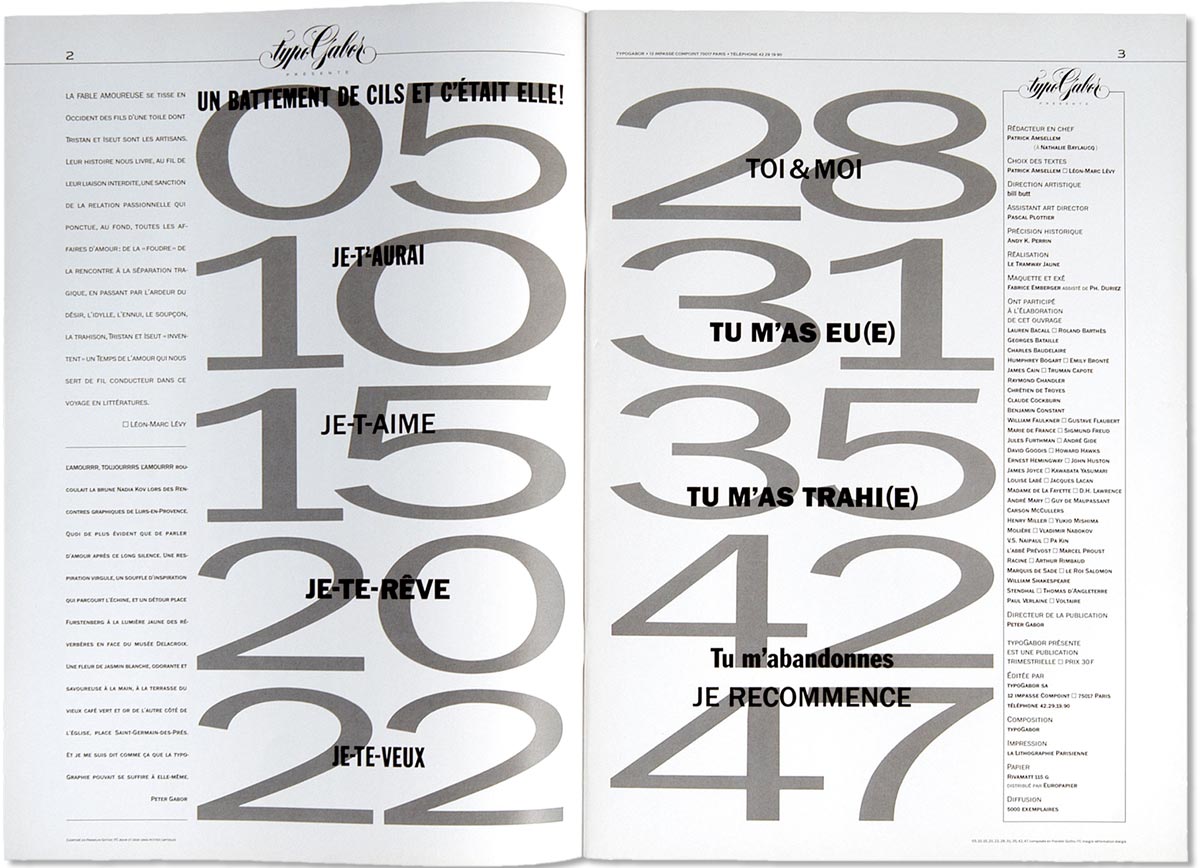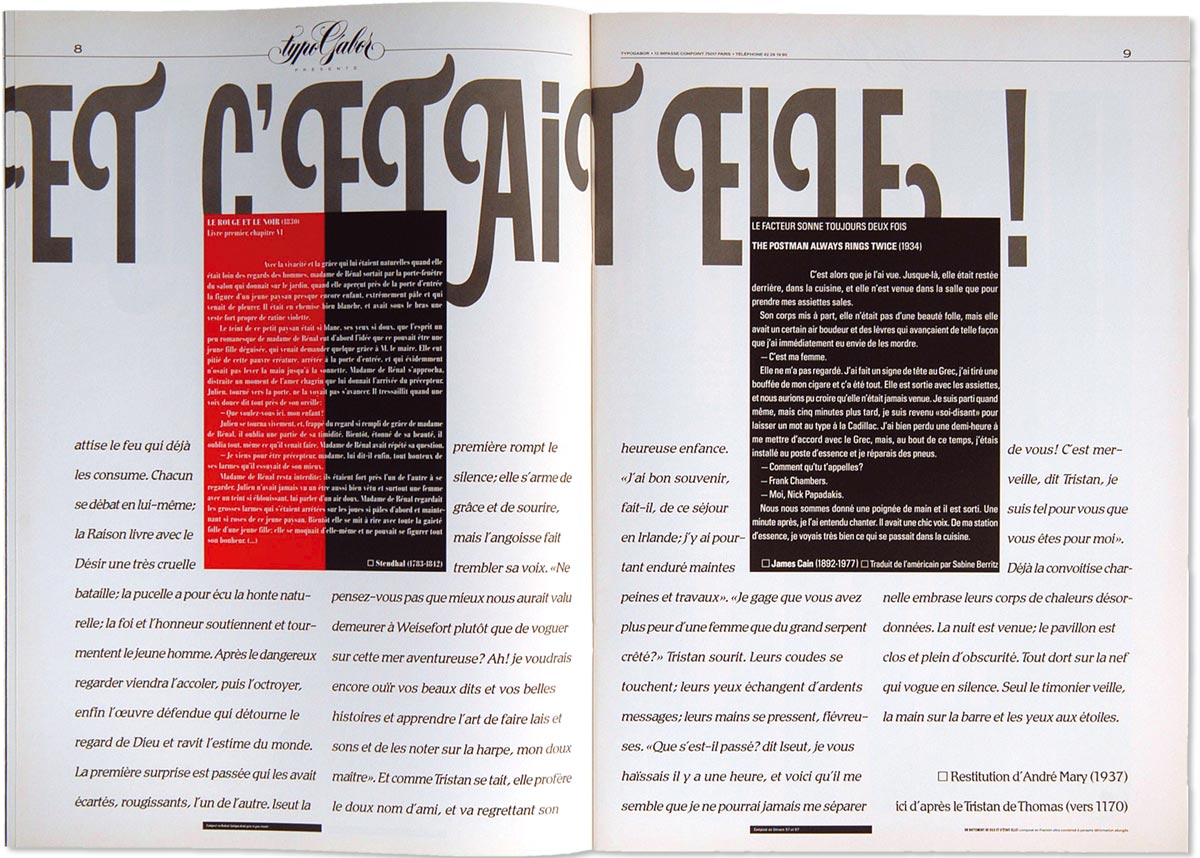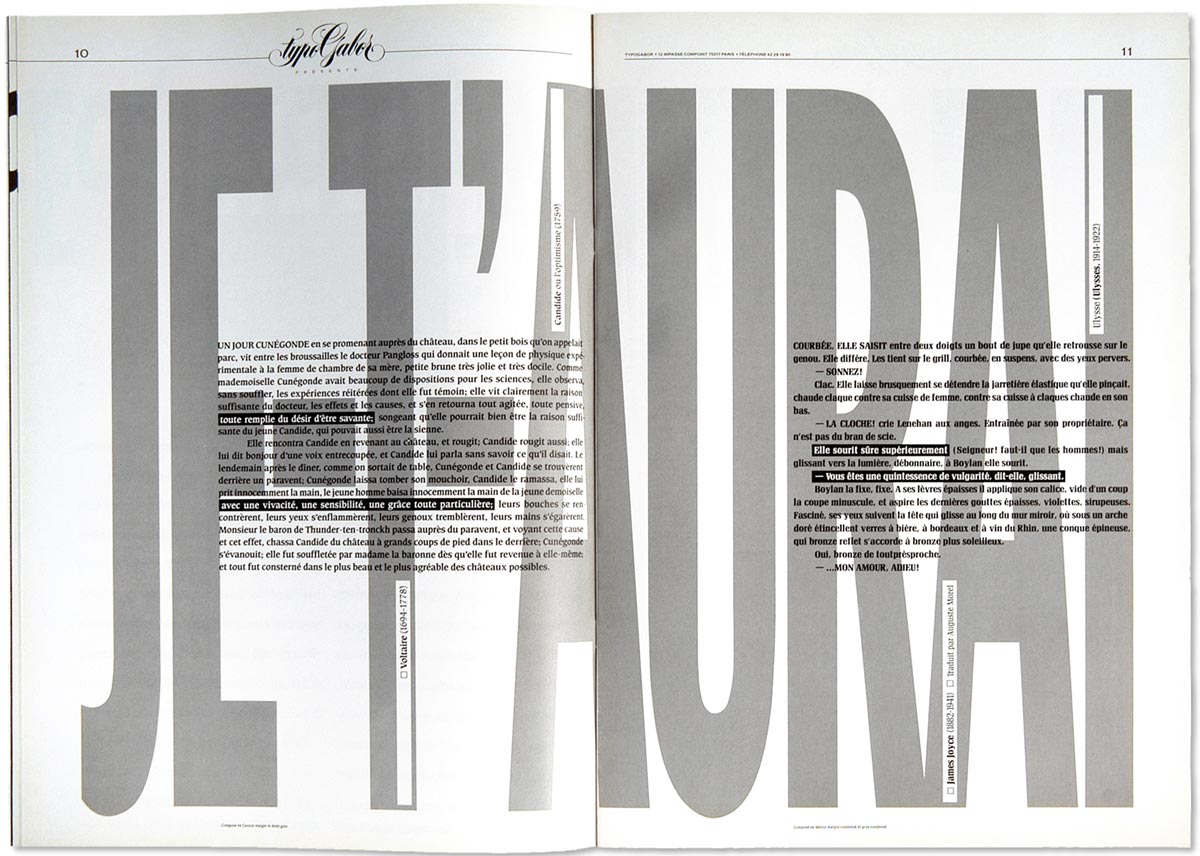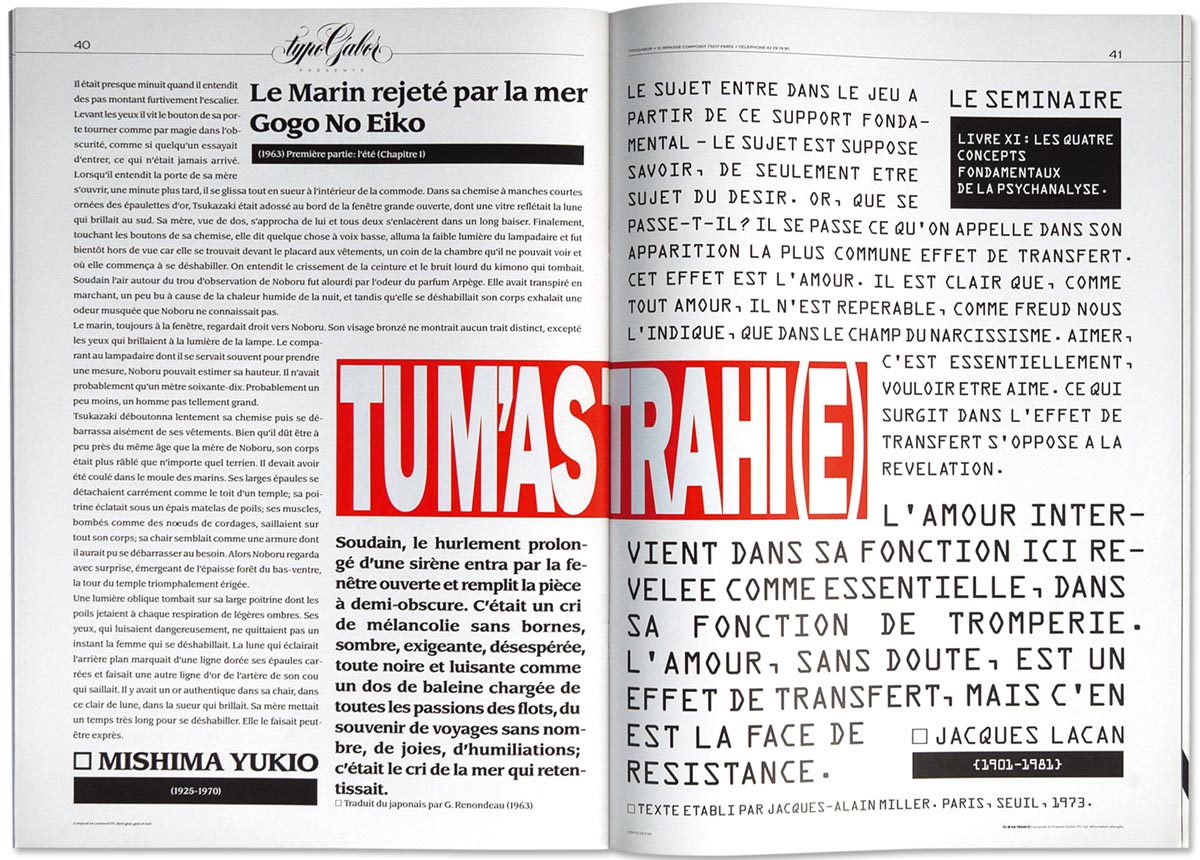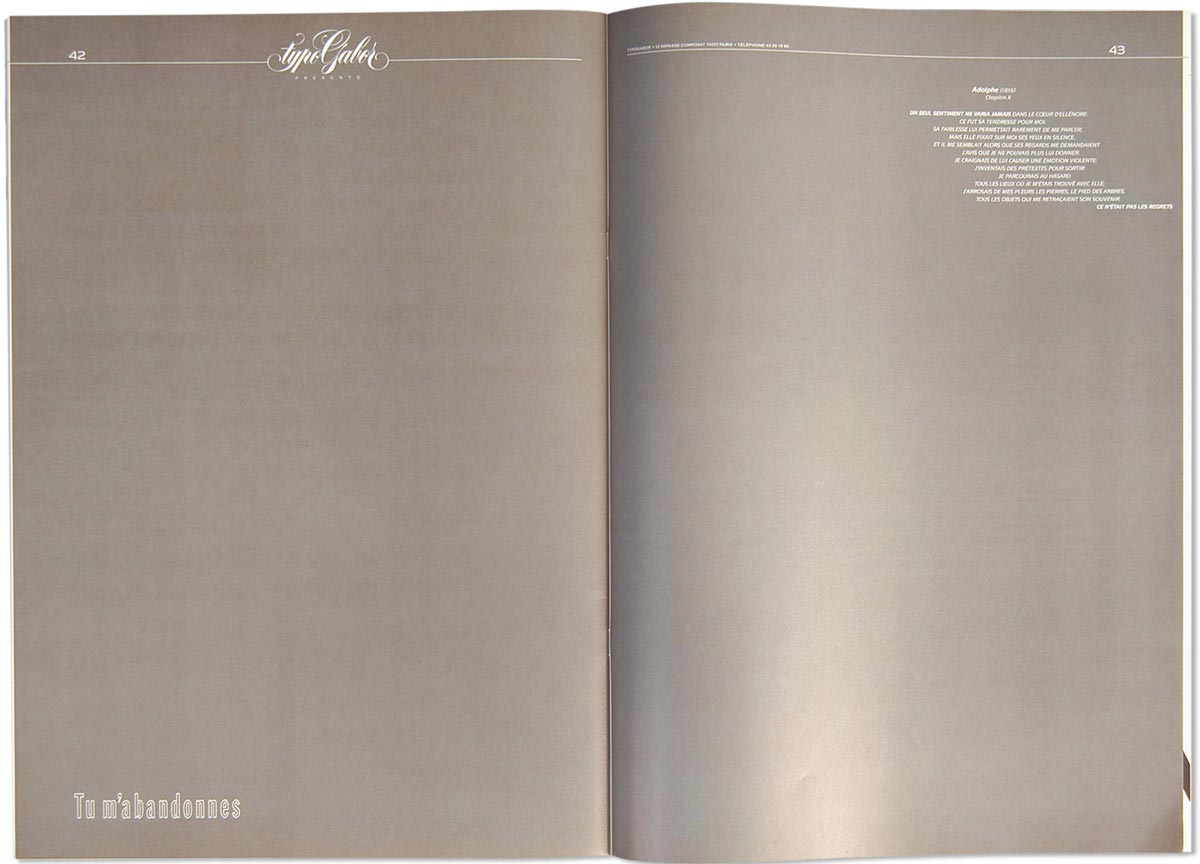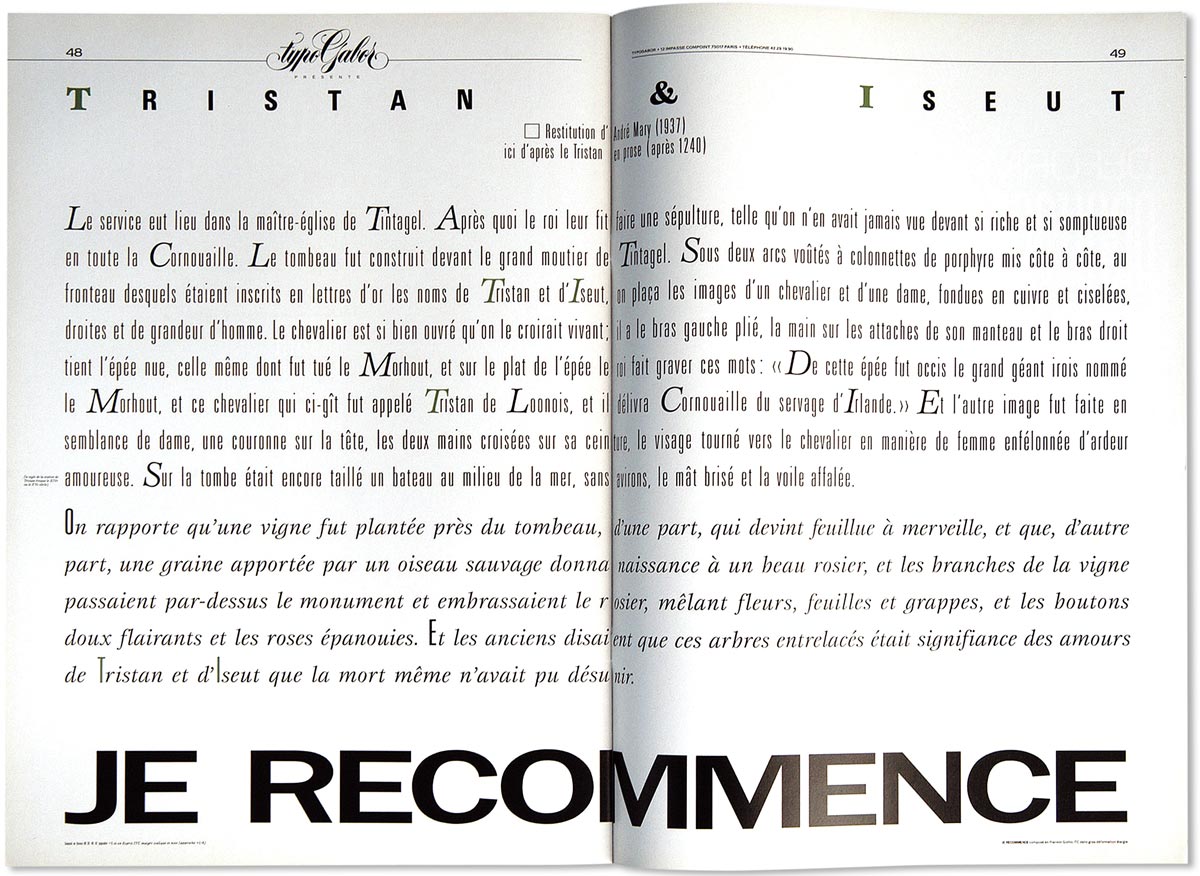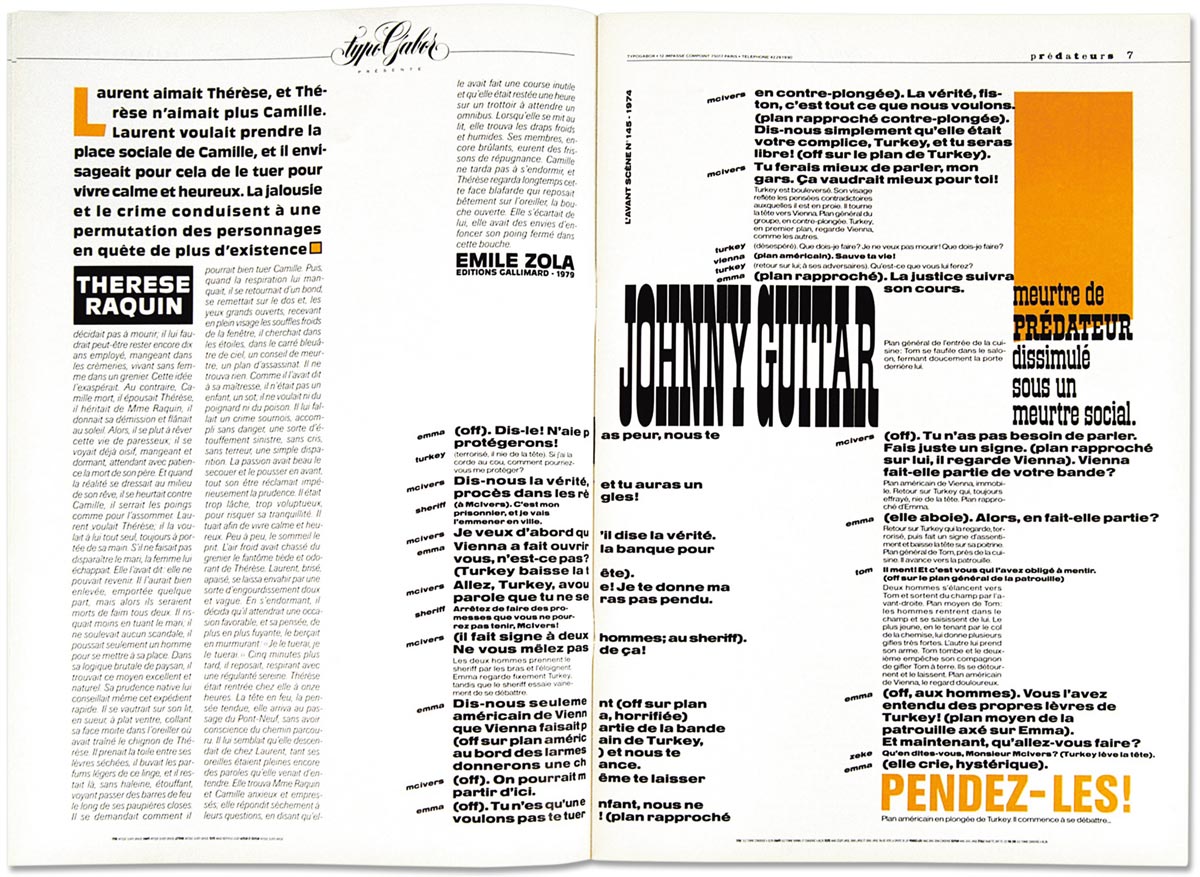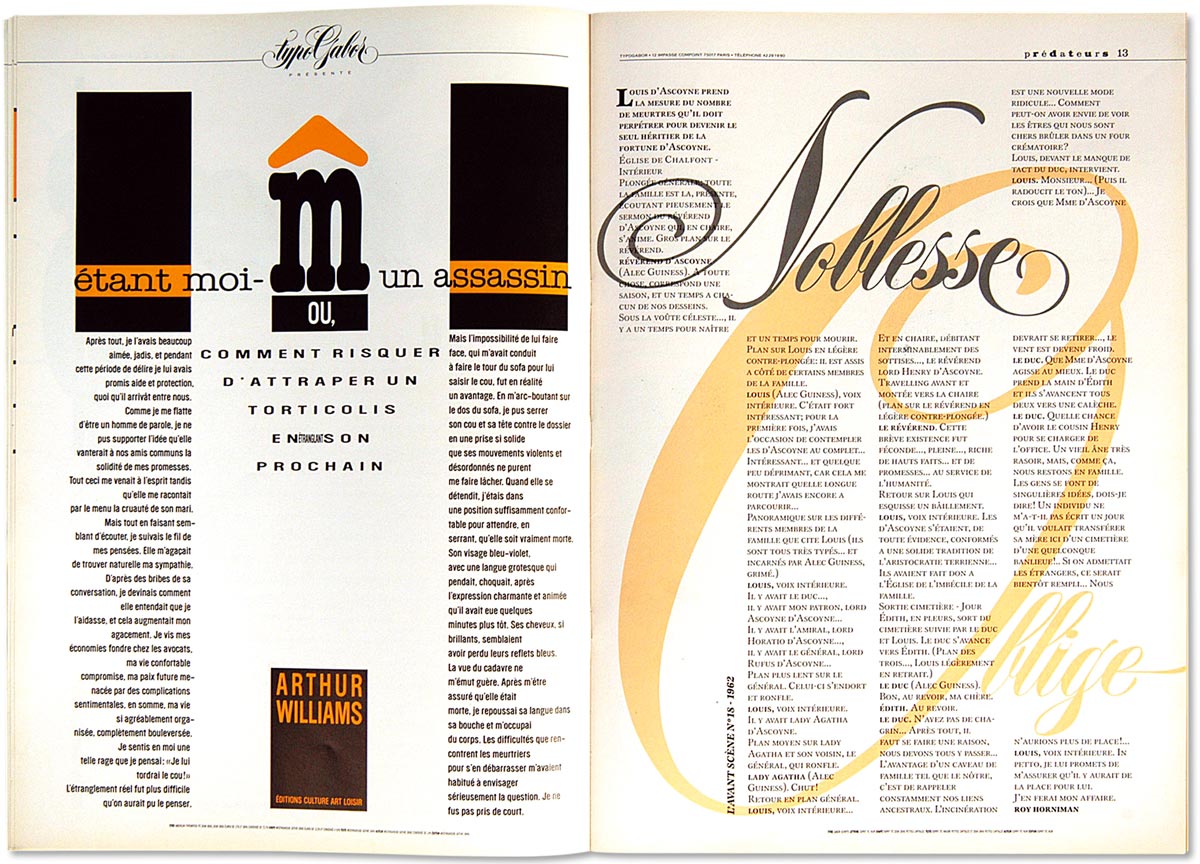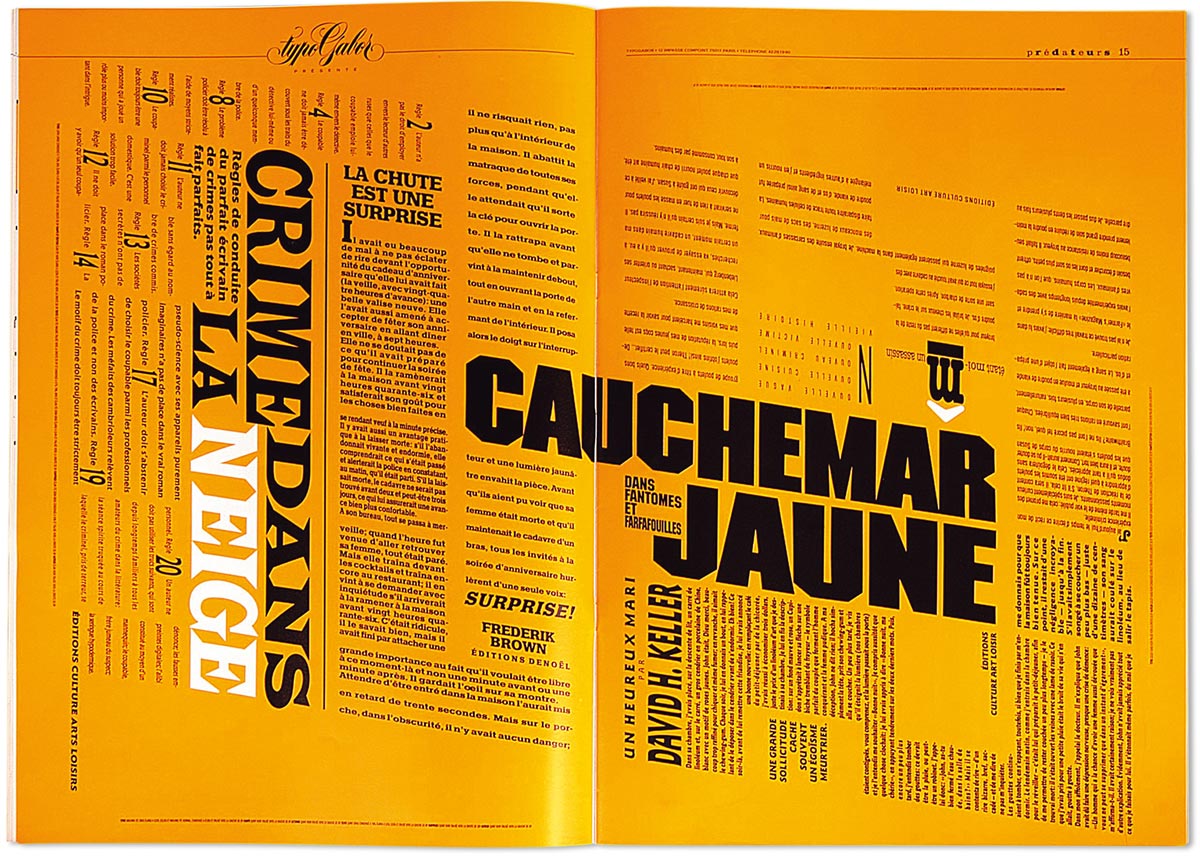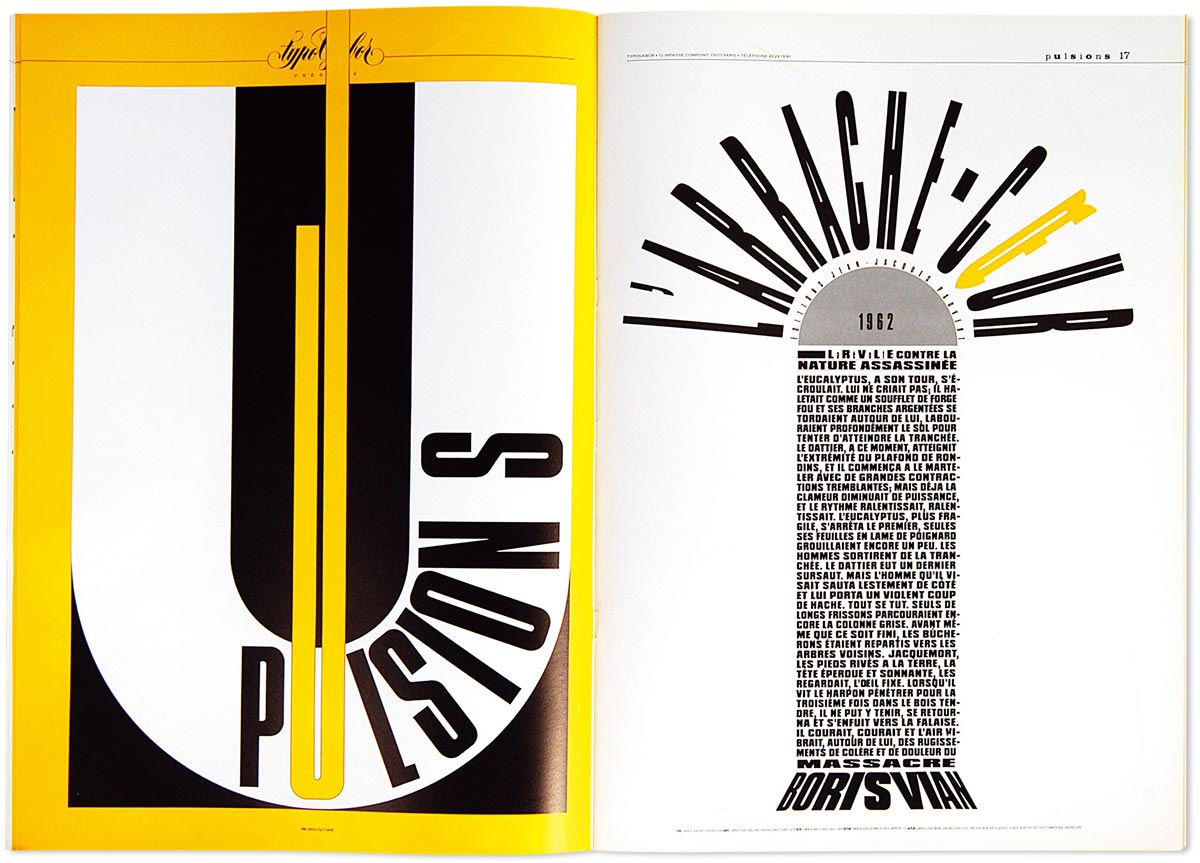
Les magazines littéraires typogabor | DaDa aussi
Lancé en novembre 1980, les premiers magazines typogabor étaient des similar too des Upper & lower case d’ITC. Formule qui a bien fonctionné pour faire connaître les collections (digitales) typographiques américaines auprès des art directors des agences parisiennes. Néanmoins le contenu et la forme de ces éditions ronronnaient de façon trop monotone si bien qu’en 1986 après une période de gestation qui a duré cinq ans, je décide le reformatage des magazines typogabor pour leur donner leur forme définitive, des magazines d’anthologie littéraire. L’idée était assez simple. Les acteurs de la communication en avaient certainement assez de voir la prolifération des caractères complètement déconnectées de tout sens. Leur mise en scène sous une forme littéraire allait leur donner une légitimité qui ne pouvait que remuer la sensibilité non seulement des art directors mais aussi bien des concepteurs rédacteurs qui fonctionnaient en team avec les premiers. Un lieu de réflexion sur le contenu et la forme typographique, ces magazines allaient remporter un vif succès.
J’ai confié la direction artistique de la première édition de cette nouvelle formule à Bill Butt (Jardin des Modes) et ensuite les suivants furent mises en scène par de jeunes graphistes sortis fraîchement de l’ESAG tel Meutres par Philippe Duriez.
C’est mon ami Léon Marc Lévy qui a assuré la rédaction en chef de la plupart de ces magazines, à l’exception de celui de Meurtres que j’ai personnellement dirigé en 1987. L’esprit DaDa soufflait sur toute l’équipe depuis la rédaction à la réalisation qui à l’époque se concrétisait entièrement en production traditionnelle (photocomposition et montages manuels des films typo sur table lumineuse). Véritables tours de force typographiques ces magazines témoignaient une fois de plus que seule la transgression permettait de véhiculer les concepts novateurs des nouvelles collections de caractères qui se multipliaient en Amérique sous l’impulsion des technologies digitales.